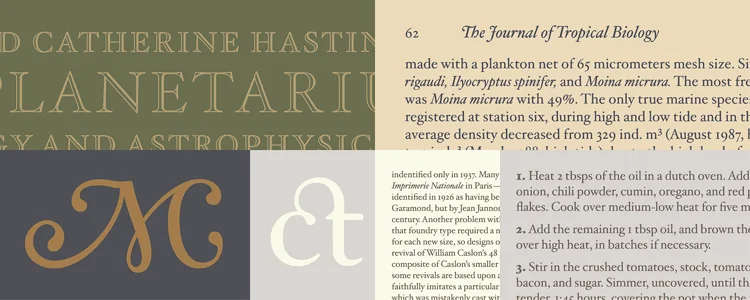
Jonathan Hoefler, grafico che ha disegnato Hoefler Text (un font che è di serie con tutti i Mac sin dal System 7.5) è stato premiato con una medaglia dall’American Institute of Graphic Arts (AIGA), insieme al suo collega e socio in affari Tobias Frere-Jones. Nella motivazione del premio si legge che questo è stato assegnato agli autori per il loro contributo “al panorama tipografico, con arte impeccabile, comprovati riferimenti storici e lucide considerazioni all’interno della comunità”.
Hoefler disegnò questo font specificatamente per Apple nel 1991. Sul sito di Hoefler & Frere-Jones il carattere in questione è definito “un classico moderno” con caratteristiche “old style”, legature estese, scritte che ricordano quelle scolpite sui capitelli nei primi anni del Novecento e arabeschi rinascimentali. Il font vanta caratteristiche come legature automatiche, la “s” lunga e rotonda, un vero e proprio maiuscoletto, “pesi” e svolazzi vari. L’Hoefler Text è anche un carattere con ornamenti intonati; è uno dei pochi font ampiamenti diffusi che include maiuscoletto corsivo, due set di maiuscole intagliate, include i numeri minuscoli, progettati per armonizzarsi con il testo standard minuscolo e maiuscolo.